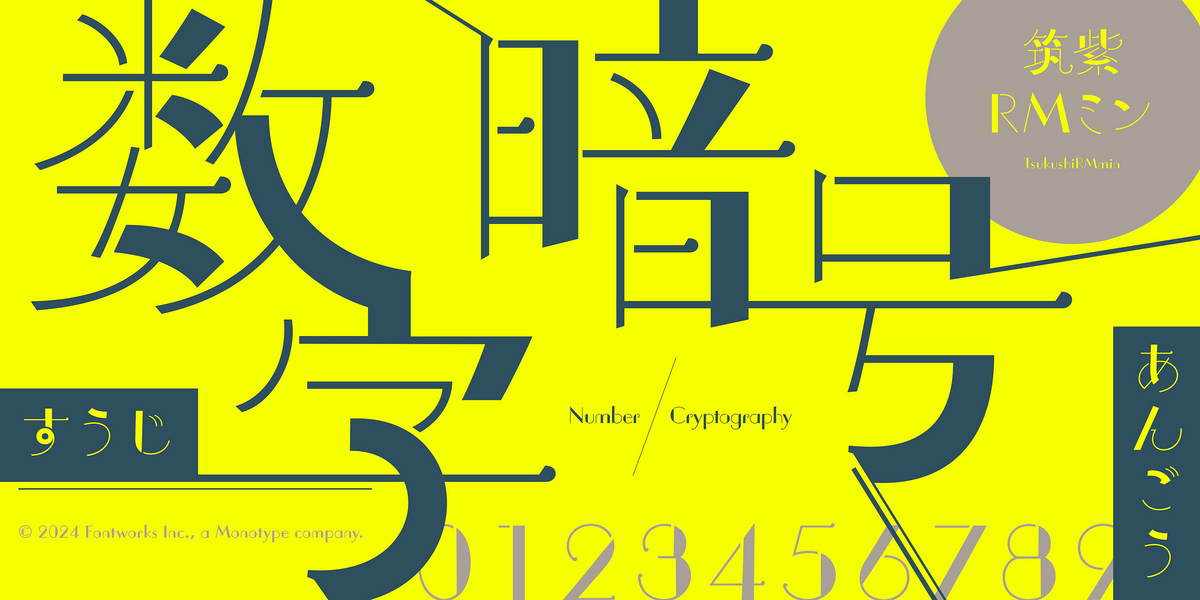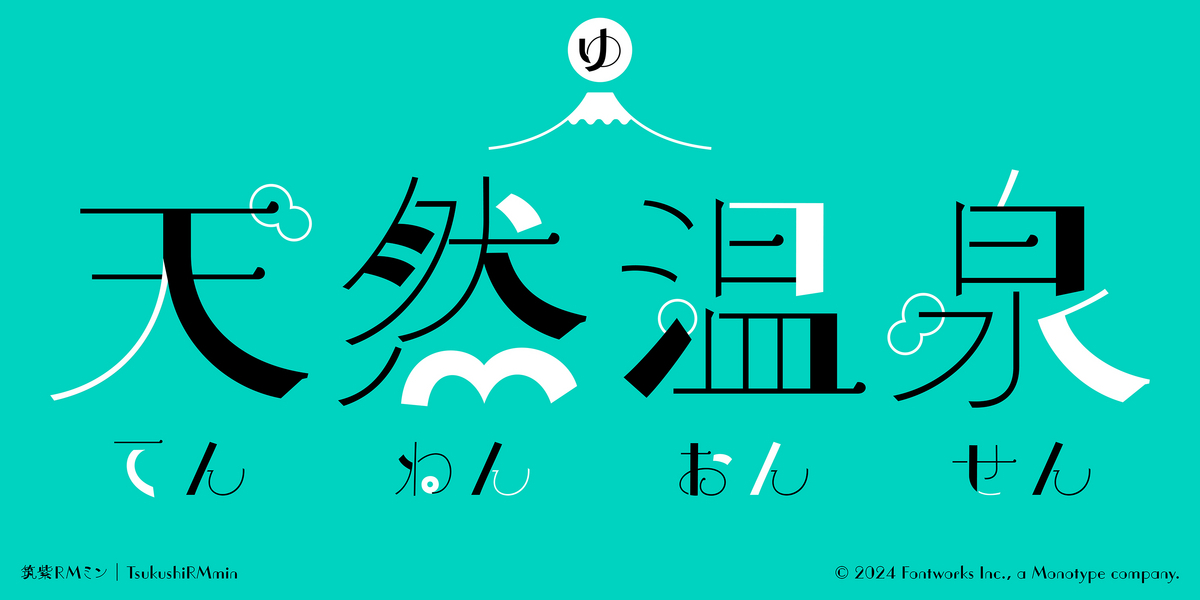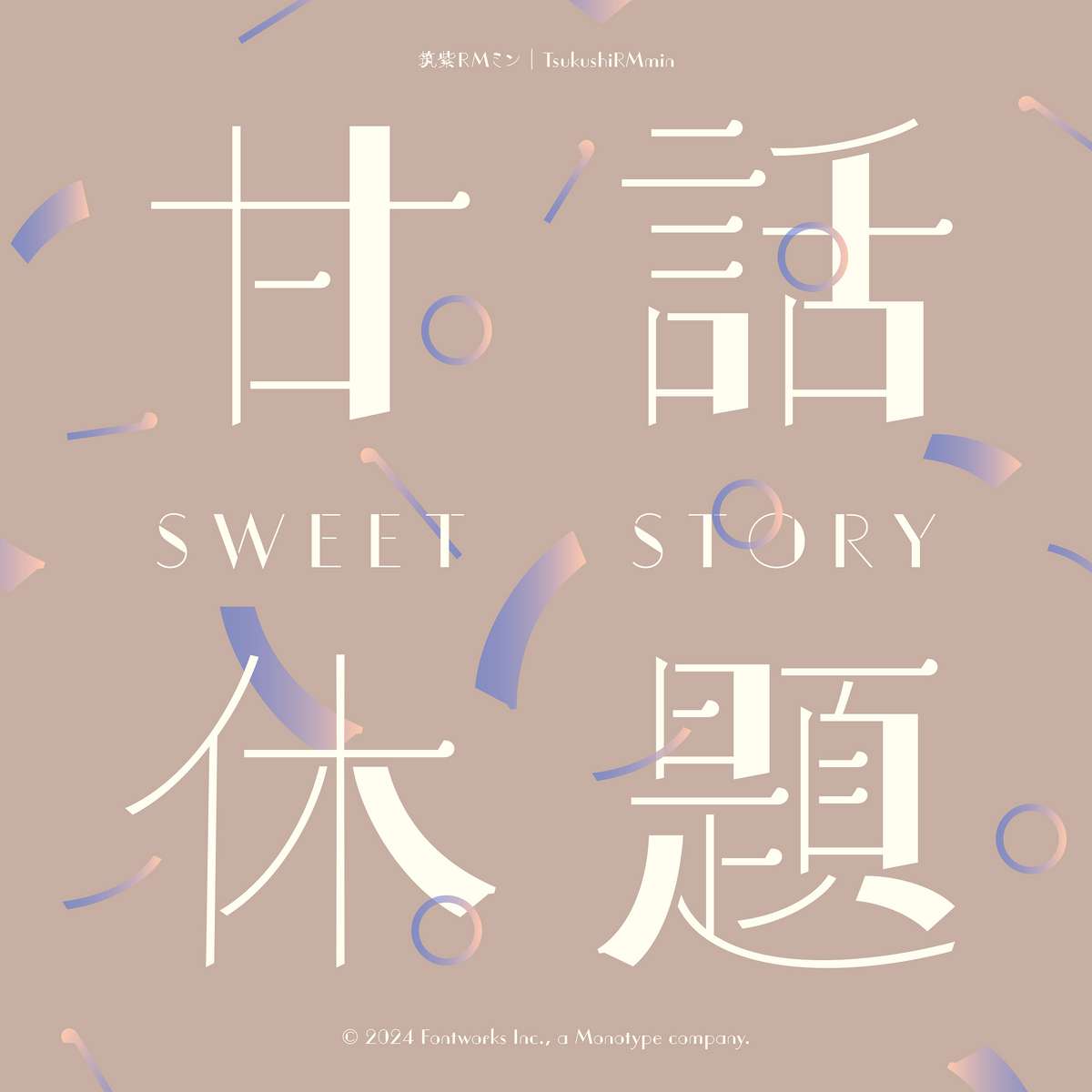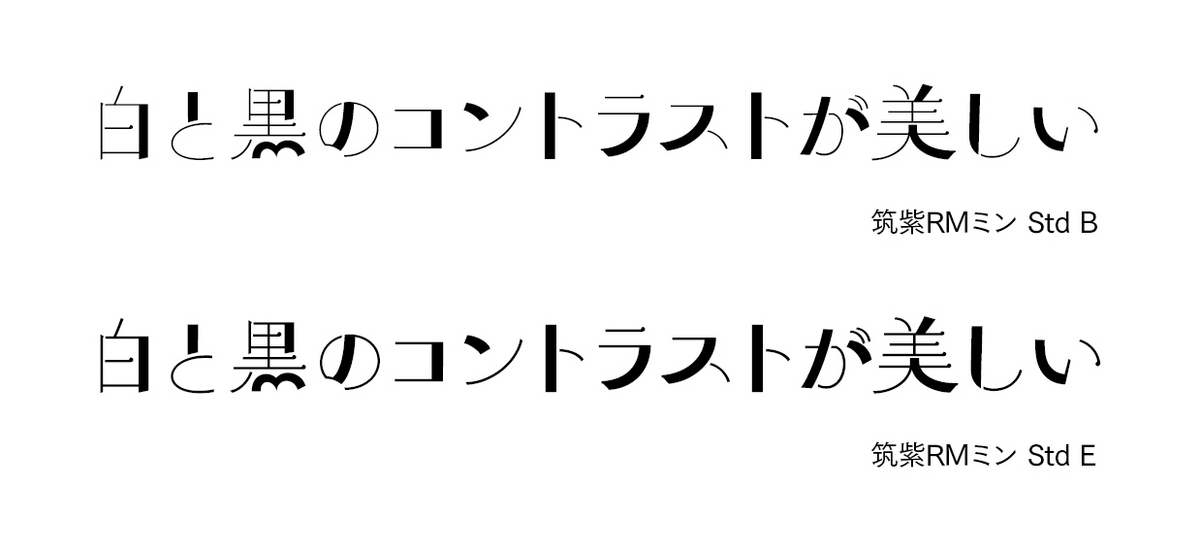
フォントワークスが藤田重信氏の新書体「筑紫RMミン」を発表
フォントワークは、2024年3月21日に、フォントワークス筑紫書体シリーズの最新作となる和文書体「筑紫RMミン Std B/E」をリリースしたことを発表した。
藤田重信Profile
1957年福岡県生まれ。1975年、写真植字機の株式会社写研文字デザイン部門に入社。1998年、フォントワークス株式会社に入社し、数多くの書体開発をする。2004年に筑紫書体を生み出し、2017年に筑紫書体シリーズがグッドデザイン賞受賞。その他多数デザイン賞を受賞。2016年、NHK「プロフェッショナル 仕事の流儀」に出演。
著書に『文字のデザイン・書体のフシギ』(2008年刊、左右社)。今年1月には新刊『筑紫書体と藤田重信』(パイインターナショナル)を発売。
筑紫RMミン
「筑紫RMミン」は、線の太さのコントラストが美しい、レトロモダンな雰囲気の書体。
ポップやカジュアルになりすぎず、クリエイティブに気品を添えながら魅力的でファンシーなイメージを体現できる。
可読性を保ちながらも遊び心があり、書籍の装丁やパッケージデザインなどの紙媒体からリリックビデオなどのデジタルコンテンツまで幅広く使用できる。
ウエイトは、BおよびEの2ウエイト展開。